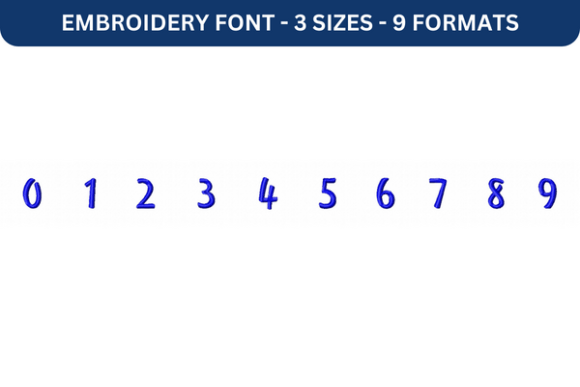
Marketing Script Font Number 0 to 9
Doğru tasarım öğelerini bulmak zor olabilir, ancak Marketing Script Font Number 0 to 9, çalışmanızı anında bir üst seviyeye taşıyan olağanüstü bir koleksiyon sunar.
İster İsteğe Bağlı Baskı (POD) ürünleri, ister düğün davetiyeleri veya sosyal medya grafikleri oluşturuyor olun, Marketing Script Font Number 0 to 9 ideal bir uyumdur.
Uzman ipucu: Pazarda öne çıkan benzersiz, göz alıcı tasarımlar oluşturmak için bu öğeleri tamamlayıcı yazı tipleriyle birleştirin.